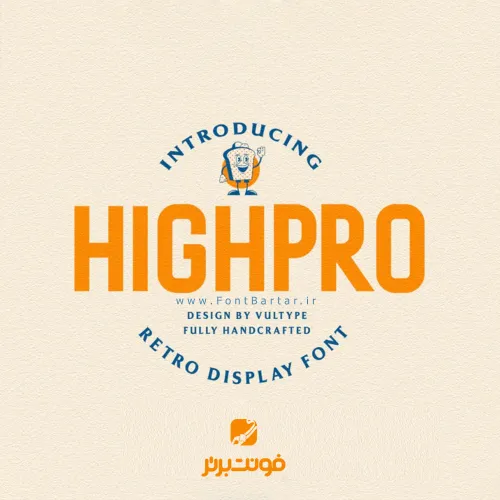
فونت انگلیسی Highpro
دانلود فونت کلاسیک Highpro
یک فونت کلاسیک سیاه با مجموعه ای از کاراککتر های شیک ، ظریف و قدیمی است – فونت Sans Serif برای پروژه های آینده شما مناسب است. مانند برند و لوگو ، طراحی های گرافیکی ، طراحی لوازم التحریر ، طراحی ورزشی ، طراحی وبلاگ ، طراحی تبلیغات مدرن ، دعوت نامه کارت ، نقل قول هنری ، دکور خانه ، عنوان کتاب / جلد ، رویدادهای خاص و موارد دیگر. فونت رایگان کلاسیک Highpro شامل فایل های Highpro OTF، Highpro TTF می باشد.
فونت انگلیسی Highpro مورد استفاده برای:
• طراحان وب سایت و گرافیست های خلاق می توانند از این مجموعه زیبا فونت در طراحی پروژه های تبلیغاتی و تجاری خود کمک بگیرند.